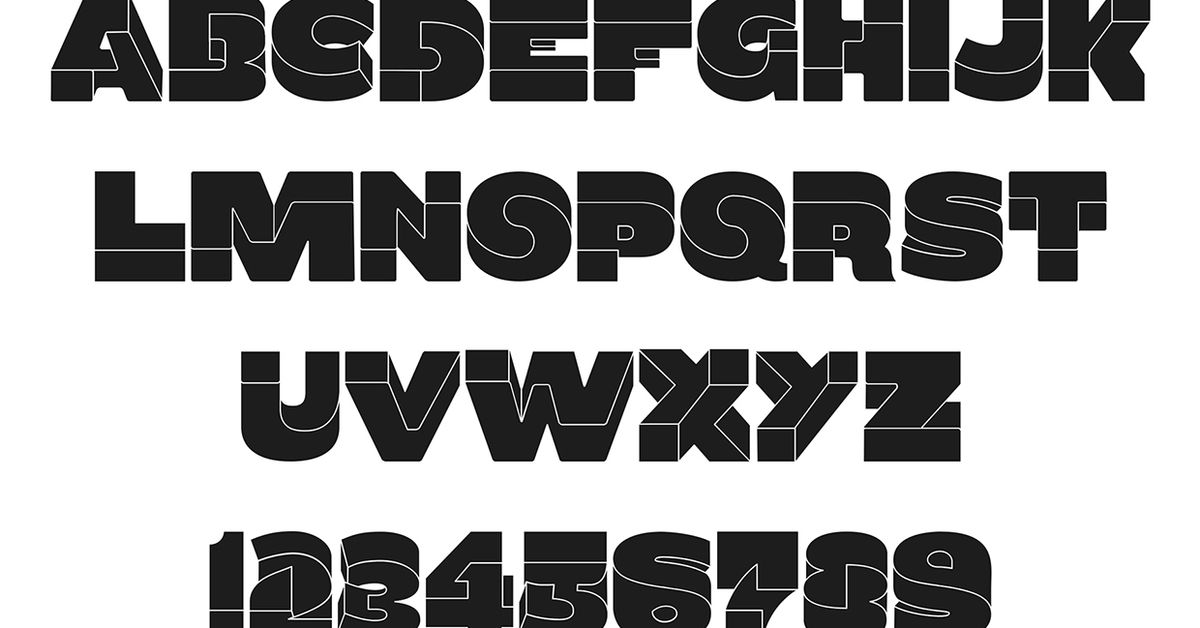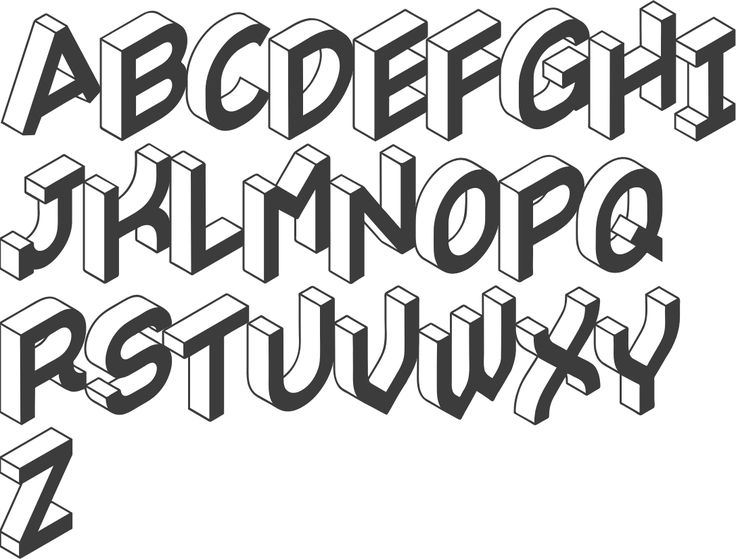
25+ бесплатных кириллических шрифтов для дизайна 2022 — PixsoDSGN на vc.ru
Шрифт — один из основных инструментов любого дизайнера. Главный тренд этого года в графическом и веб-дизайне – крупные высокие заголовки, написанные заглавными буквами. Этот прием одинаково эффектно смотрится в оформлении сайта, соцсетей, рекламных баннеров, лид-магнитов, каталогов.
Мы постарались выбрать самые хорошие из бесплатных шрифтов с кириллицей, опубликованных в 2022. Шрифты проверены на поддержку кириллицы и доступны для скачивания.
1. Golos
Универсальный закрытый гротеск, разработанный по инициативе компании Смена (группа AIC) . Он хорошо подходит для чтения длинных текстов с экрана и рекомендуется для сайтов государственных и социальных сервисов. Текстовая линейка включает пять начертаний разной жирности от Regular до Black. Дизайнеры — Александра Королькова и Виталий Кузьмин.
Golos Text — универсальный закрытый, хорошо подходит для чтения длинных текстов с экрана и рекомендуется для государственных сайтов и социальных сервисов.
Golos UI — униширинный гротеск, который благодаря чуть зауженным пропорциям, идеально подходит для использования в элементах интерфейсов. Свойство фиксированной ширины знаков (Uniwidth) позволяет сохранять длину строки, при работе с начертаниями разной насыщенности.
2. frankinity
Шрифт frankinity высокий шрифт с засечками.
3. Neue Machina
Neue Machina — бесплатный вариативный гротеск с кириллицей, выпущенный Pangram Pangram. Презентацию оформил Васьен Катро aka Baugasm. Обратите внимание — ловушки для чернил (inktraps) вошли в моду.
4. Lack
Lack —это смелый, современный и экспериментальный шрифт, который поставляется в одной насыщенности с курсивом. Принадлежит к семейству Lack Family, начертание Regular.
5. Bebas Neue
Бебас — самый популярный во всем мире прописной шрифт стал «Гельветикой свободных шрифтов». Выпущенный в 2010 году Bebas Neue используется как крупными компаниями, так и начинающими дизайнерами для многих проектов. Новые начертания остаются верными стилю и изяществу Bebas со знакомыми чистыми линиями, элегантными формами, сочетанием технической прямоты и теплой простоты. Семейство Bebas Neue одинаково уместно для веб, печати, коммерции и искусства. Ему делают регулярные обновления, а в 2019 вышел долгожданный платный Bebas Neue Pro со строчными буквами и наклонными начертаниями. Но если вы пользуетесь шрифтами Adobe (включенными в Adobe Creative Cloud) , можно использовать все семейства Bebas бесплатно!
Дизайнер Ryoichi Tsunekawa. Количество глифов 486.
6. Bitter
Bitter — современный шрифт с засечками для текста, специально разработанный для комфортного чтения на любом компьютере или устройстве. Сделан на основе пиксельной сетки и скорее на рациональных, а не эмоциональных принципах. Он сочетает в себе большую высоту строчных, разборчивость гуманистической традиции и тонкие характеристики символов. Начертание Regular несколько толще, чем обычный стиль «Regular» для печатного дизайна. Это создает интенсивный цвет в абзацах, подчеркнутый толстыми засечками. Вариативность позволит подобрать необходимое начертание, а размер строки останется прежним. Каждый глиф тщательно проработан с превосходным качеством кривых и полностью соответствует пиксельной сетке. Шрифт сбалансирован и расставлен вручную, чтобы использовать очень мало пар кернинга, что особенно важно для веб-шрифтов, поскольку большинство браузеров в настоящее время не поддерживают эту функцию.
Разработан Солом Матасом для Huerta Tipográfica. Количество глифов 1475.
7. Spectral
Spectral — текстовый шрифт, обращающийся к истории французского шрифтового дизайна, но современный и универсальный, хорошо подходящий для чтения с экрана: Spectral разрабатывался в первую очередь как шрифт для Google Docs и Google Sheets — офисных инструментов для совместной работы. У него характерные для динамической антиквы контраст, открытость знаков и оси овалов. Есть ещё родственный капительный шрифт Spectral SC с таким же набором начертаний.
Кириллица в шрифте качественная и сбалансированная, с хорошо применёнными конструкциями и решениями.
Нарисован Ильей Рудерманом и Юрием Остроменцким из type. today. Количество глифов 145.
8. Aqum two
Акум 2 — это минималистичный геометрический гротеск с закругленными углами и концами. Выделяется за счет очень дружелюбного вида. Начертание Classic — простой шрифт в котором все буквы заглавные. Дизайнер Slava Antipov.
Издатель Slava Antipov. Количество глифов 247.
9. Concrete
Concrete — Акцидентный гротеск с необычными формами и отличной читабельностью от Андрея Картера. Concrete подходит для заголовков, плакатов, логотипов, графического дизайна, веб-сайтов, резюме, дизайна продуктов, специальных мероприятий или всего, где нужна рукописная и умеренно брутальная манера. Количество глифов 215.
10. Mont
Mont — сбалансированный, характерный Mont с уникальными деталями, такими как заостренная буква «t» и заметная высота строчных, делает его идеальным для сильных заголовков и выдающихся логотипов. В настоящее время №17 в списке лучших шрифтов MyFonts. Mont оснащен рядом таких функций OpenType как табличные фигуры, лигатуры, дроби, формы с учетом регистра, надстрочные и подстрочные знаки и т. д. Универсальность и достоинства шрифта позволяют легко решать любые задачи графического дизайна — веб, печать, моушн-графика и т. д.
Дизайнеры Svetoslav Simov, Mirela Belova. Издатель Fontfabric. Впервые опубликован на MyFonts 16 января 2018 года. В бесплатной версии набор глифов ограничен.